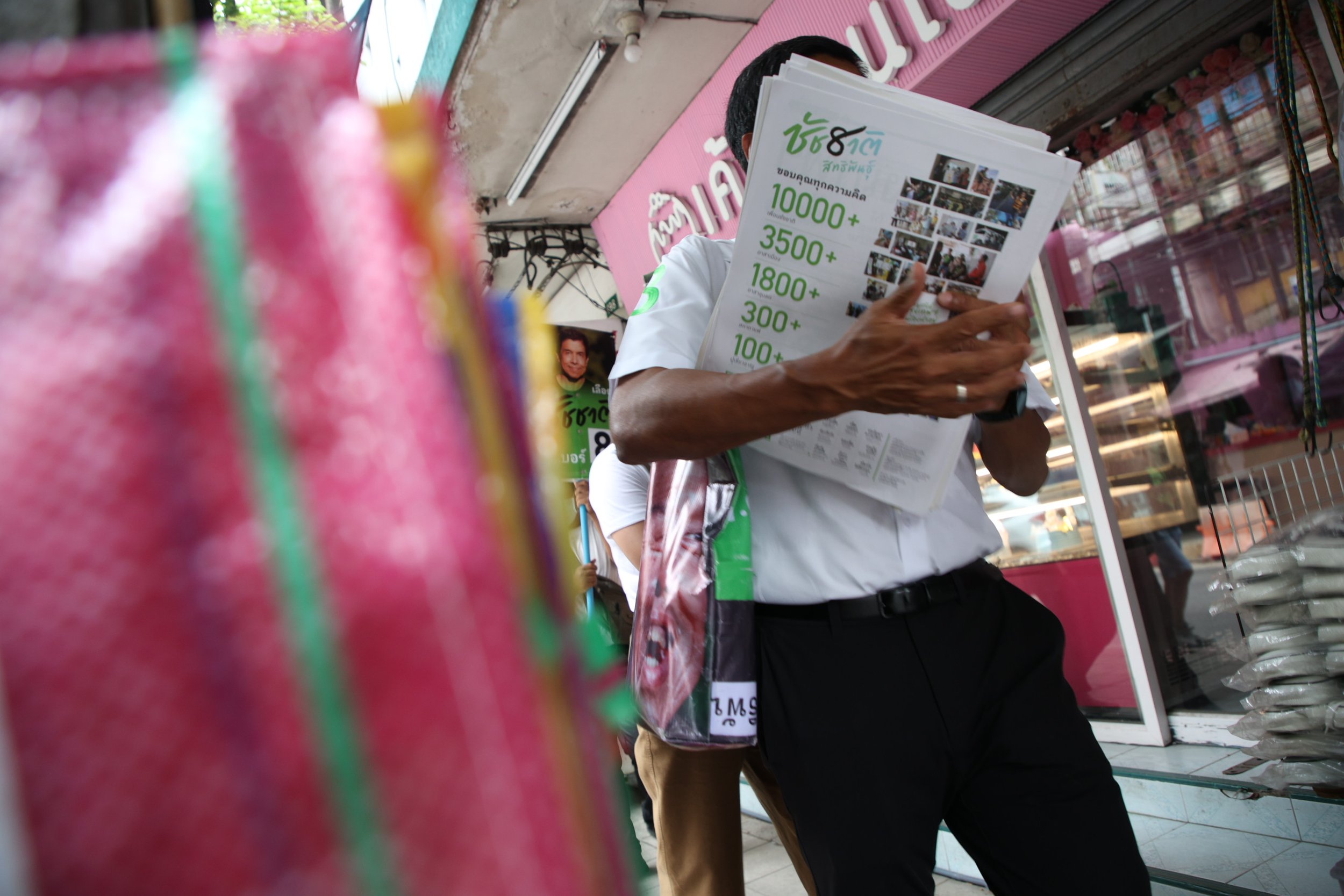
ชัช8าติ
โลโก้ผู้สมัครรับเลือกตั้งผู้ว่าราชการกรุงเทพฯ เบอร์ 8 คุณชัชชาติ สิทธิพันธ์
เช้าวันที่ 31 มีนาคม 2565 หลังจากการจับฉลากเบอร์ผู้สมัคร เราหารือกันในทีมเกี่ยวกับไอเดียที่จะทำโลโก้ชื่อผู้สมัครผสมกับตัวเลข เมื่อตกลงกันว่าจะเลือกทำให้ผู้สมัครที่เราตั้งใจจะลงคะแนนให้เป็นคนแรก บรีฟก็มีเพียงแค่ “ทำ ช ช้าง ให้เป็นเลข 8” เพราะในชื่อคุณชัชชาติ มี ช ช้าง ให้เล่นตั้ง 3 ตัว
และนี่คือผลลัพธ์
หลังจากที่โพสต์ลงโซเชียลมีเดียไปไม่นาน ทีมงานของคุณชัชชาติก็ติดต่อมาหาเรา ก่อนที่คุณชัชชาติจะโทร.มาคุยกับเราด้วยตัวเองในช่วงหัวค่ำ เพื่อขออนุญาตนำไปใช้ในแคมเปญหาเสียง แน่นอนว่าเราไม่ปฏิเสธ และยังยินดีอย่างยิ่งที่งาน fan art จะถูกนำไปใช้ในงานจริง นอกจากนั้นยังประทับใจที่คุณชัชชาติเห็นคุณค่าของงานออกแบบในฐานะทรัพย์สินทางปัญญาอีกด้วย
และนี่คือผลงาที่ทีมงานคุณชัชชาตินำโลโก้ “ชัช8าติ” ไปใช้งานตามสื่อต่างๆ